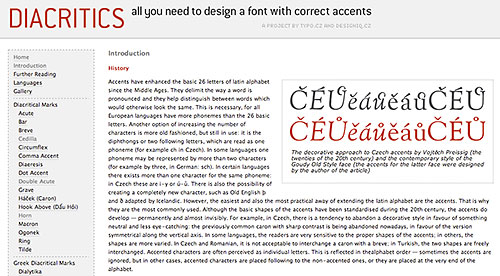
Die Welt der Akzente begreifenIn fast allen Sprachen dienen Akzente dazu, die
Einsatzmöglichkeit der 26 Buchstaben zu erweitern. Leider nicht im
Englischen, der dominierenden Sprache des Computerzeitalters, mit der Folge,
dass die Haken und Ösen der lateinischen Schriften immer wieder Probleme
bereiten. Bei der Integration der diakritischen Zeichen in Computerfonts,
also der Methode des Zusammenfügens von Buchstabe und Akzent, gibt es
gestalterische und technische Spielregeln, die eine ausgezeichnete tschechische
Die Seite Diacritics ist ein Wiki, zu dem jeder sein
Wissen beisteuern kann. Das Forum, ein Gemeinschaftsprojekt von typo.cz und dem
Designbüro designiq.cz, ist eine ausgezeichnete Quelle
für Schriftentwerfer, aber auch Schriftbenutzer, die zum Beispiel wissen
müssen, in welcher Sprache welche Akzente eingesetzt werden. Die Liste der
37 dargestellten Sprachen reicht von Albanisch (Akzente: Ç
Ë ç ë) bis zur Sprache der nigerianischen Ethnie
Yoruba (Akzente: Á Â Ǎ É Ê Ě
Ẹ Ệ Í Î Ǐ Ó Ô Ǒ Ọ á
â ǎ é ê ě ẹ ệ í î ǐ
ó ô ǒ); Akzentweltmeister ist die lateinische Umschrift
des Vietnamesischen mit den Akzenten À Á Â Ầ
Ấ Ẫ Ẩ Ậ Ã Ă Ằ Ắ Ẵ Ẳ
Ặ Ả Ạ Đ È É Ê Ề Ế Ễ
Ể Ệ Ẽ Ẻ Ẹ Ì Í Ĩ Ỉ Ị
Ò Ó Ô Ồ Ố Ỗ Ổ Ộ Õ
Ỏ Ơ Ờ Ớ Ỡ Ở Ợ Ọ Ù Ú
Ũ Ủ Ư Ừ Ứ Ữ Ử Ự Ụ Ỳ
Ý Ỹ Ỷ Ỵ à á â ầ ấ
ẫ ẩ ậ ã ă ằ ắ ẻ ẳ ặ
ả ạ đ è é ê ề ế ễ ể
ệ ẽ ẻ ẹ ì í ĩ ỉ ị
ò ó ô ồ ố ỗ ổ ộ õ
ỏ ơ ờ ớ ỡ ở ợ ọ ù ú
ũ ủ ư ừ ứ ữ ử ự ụ ỳ
ý ỹ ỷ ỵ) ... Hey, die sehen alle piekfein aus hier
in meinem Editor und im Browser ... sicher ein Verdienst von Microsofts
ausgezeichneter, weltumspannender Schrift Verdana; für eventuelle
Abstürze in anderen Systemen als Apple Mac OS 10.4 und Safari kann ich
leider keine Haftung übernehmen.